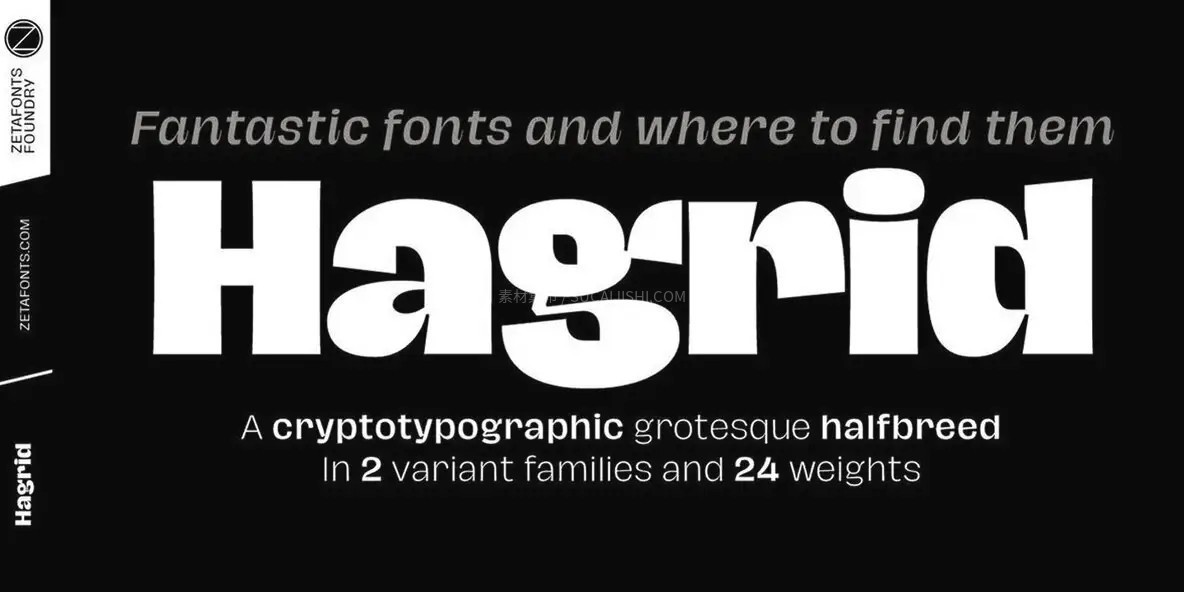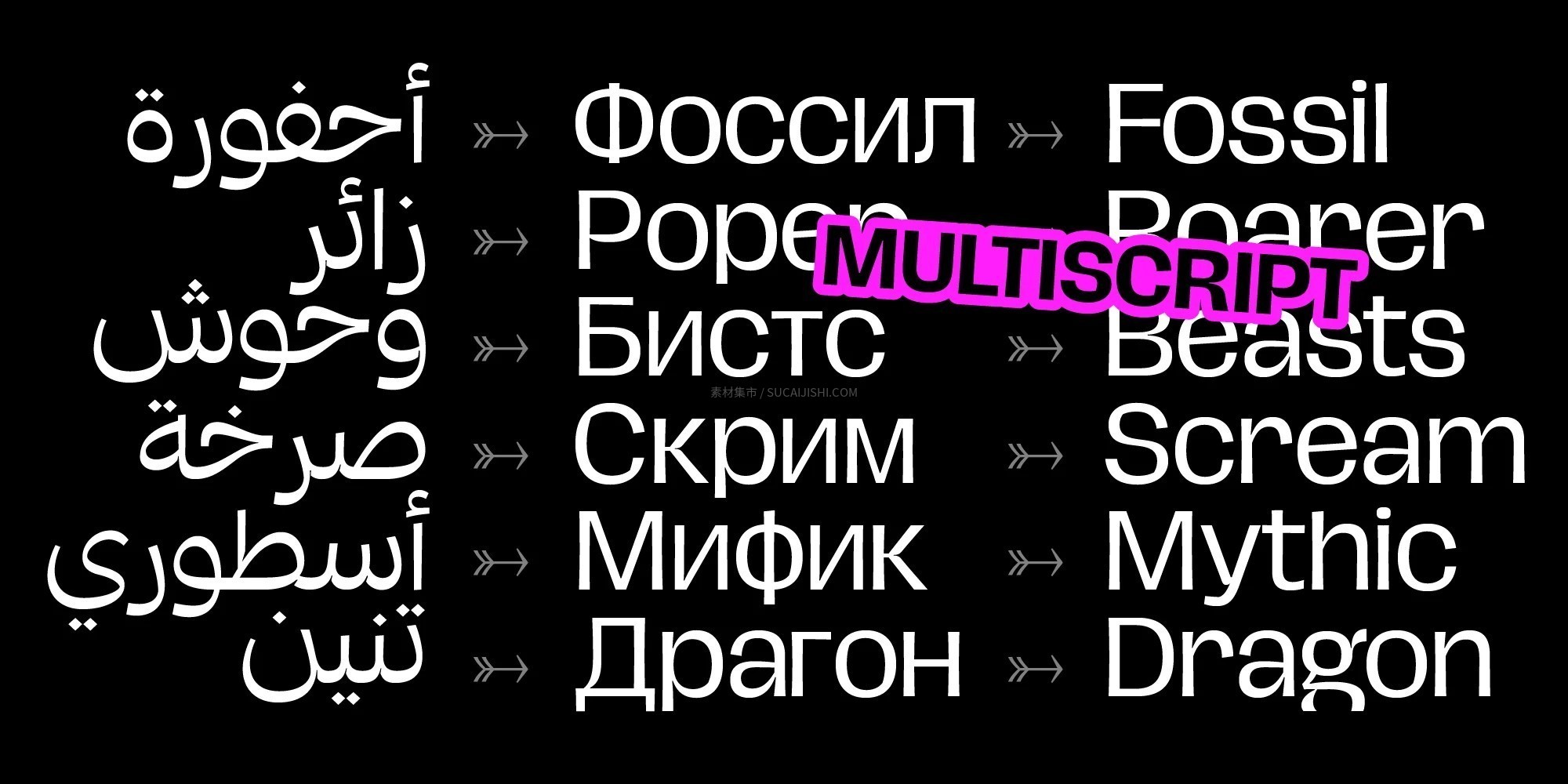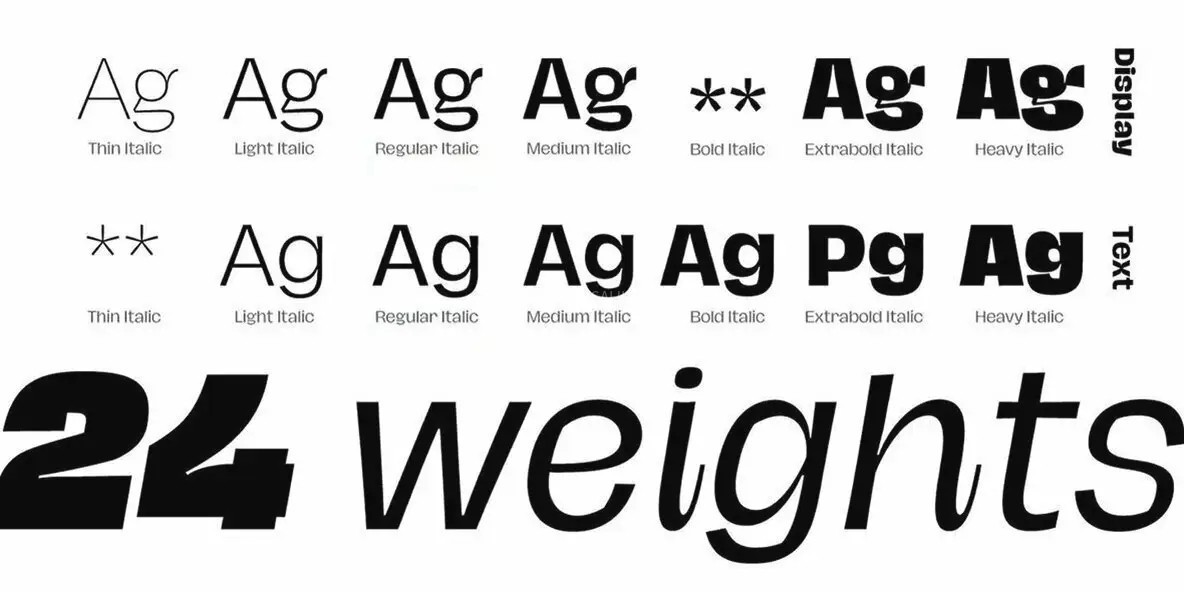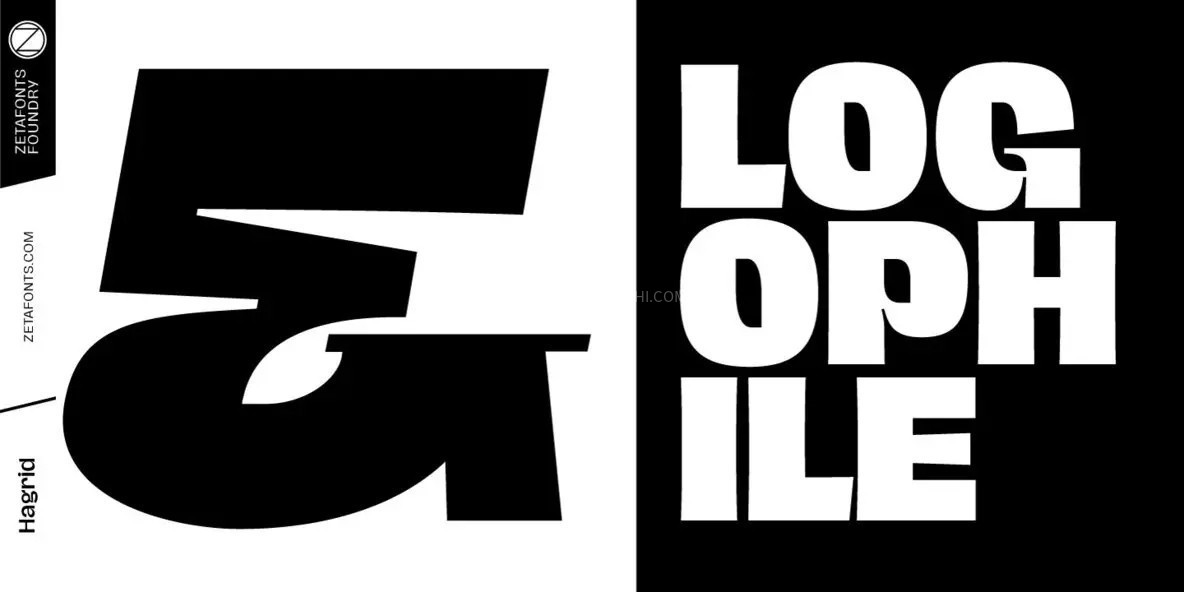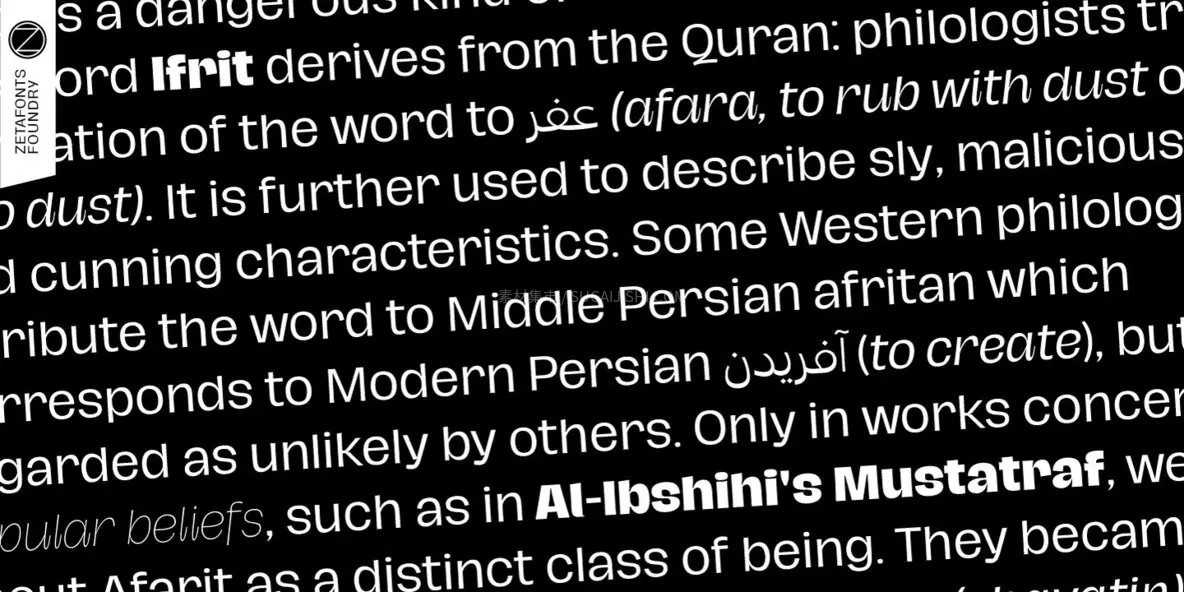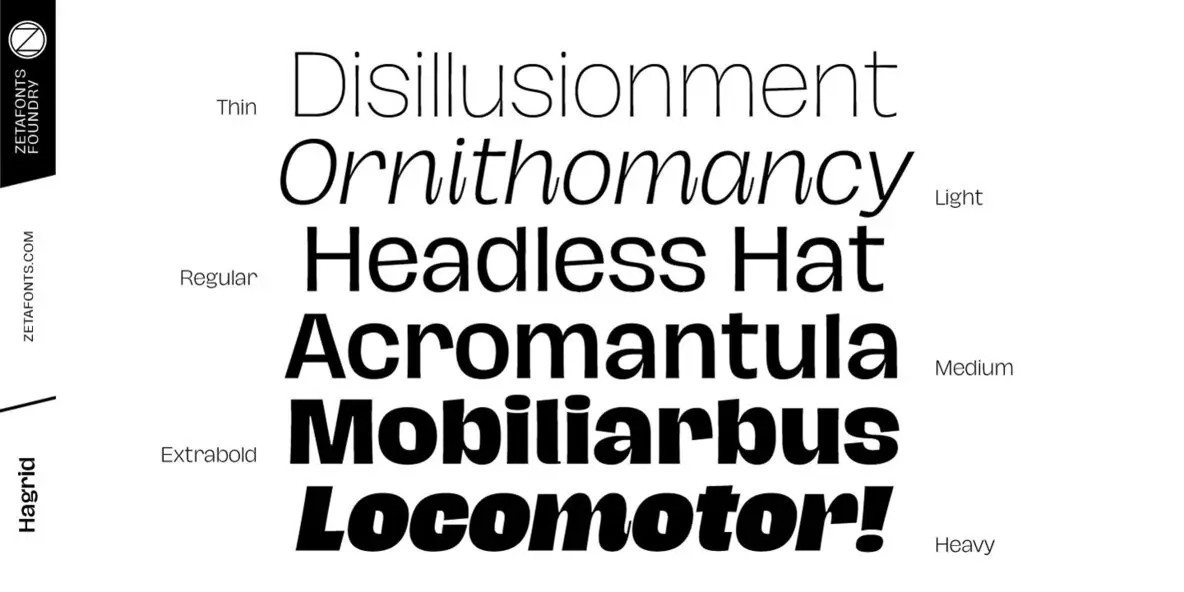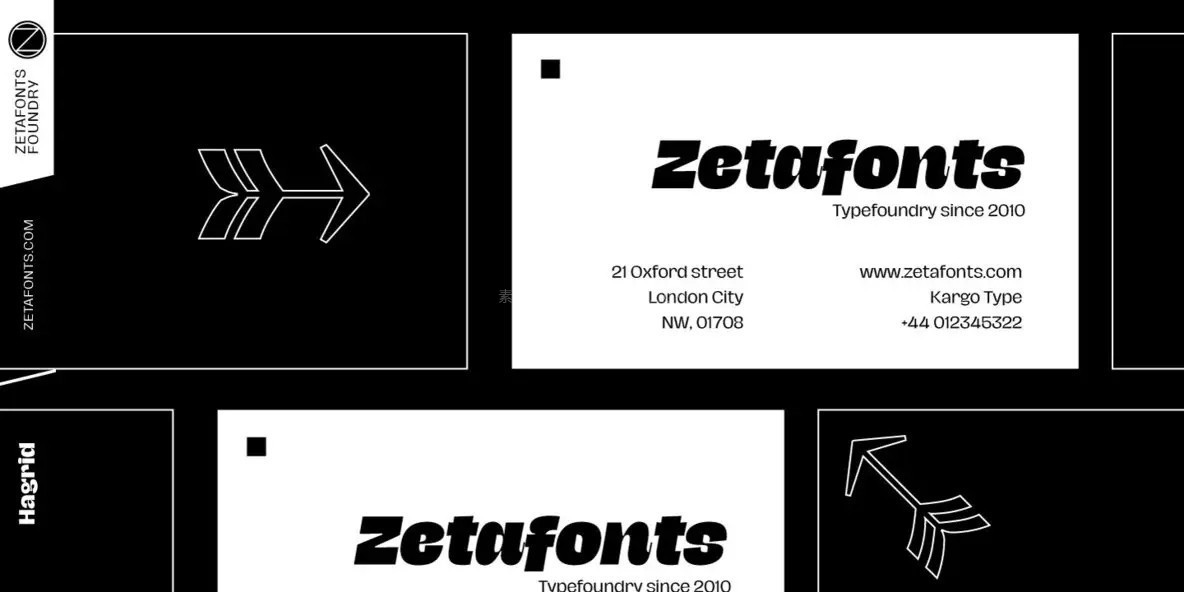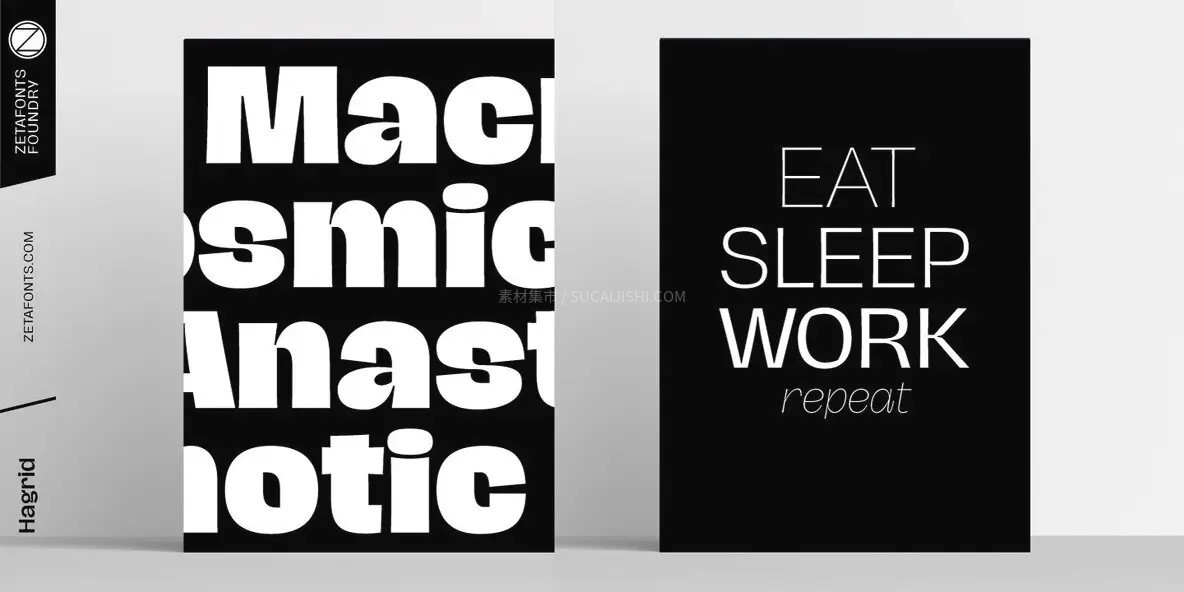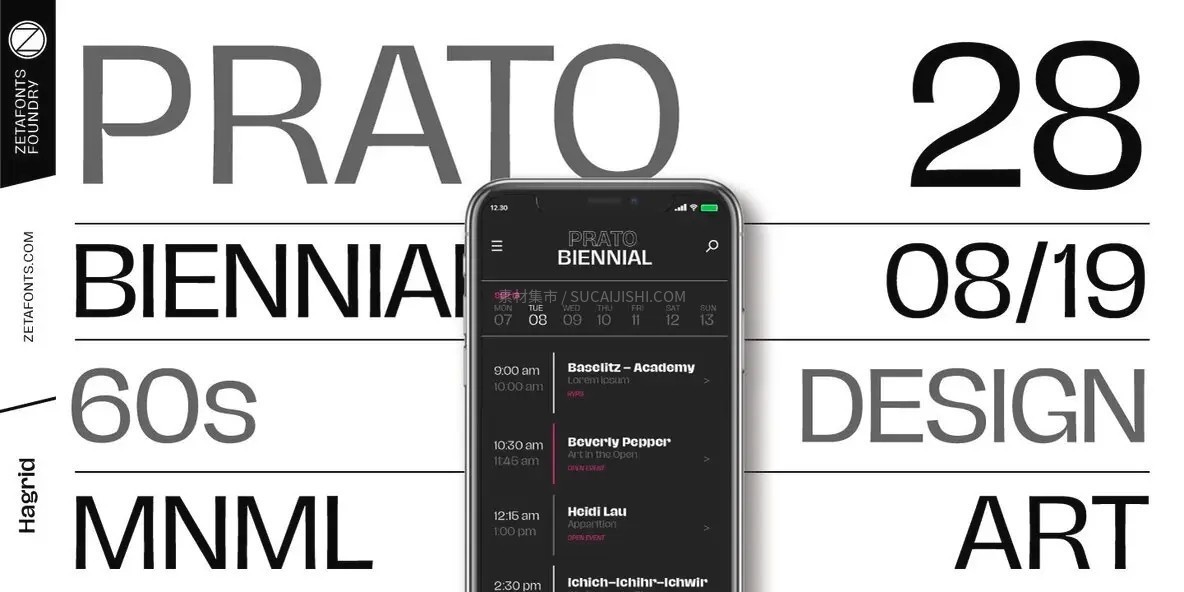
Hagrid高端品牌形象(VI)设计阿拉伯字体家族
这套神仙级的 Hagrid 超级字体家族!由知名设计师 Cosimo Lorenzo Pancini 倾情打造,整套足足包含 71 种样式和 7 款可变字体,完美支持拉丁文、阿拉伯文和西里尔字母!它巧妙融合了怪诞的字母结构、极具呼吸感的书法留白以及粗犷的对比反差,视觉冲击力直接拉满。不管是做高端品牌推广、杂志编辑排版,还是极具个性的数字媒体设计,用它都能轻松打造出大胆又独特的艺术张力!排版控和字体迷绝对不能错过的顶级字库~